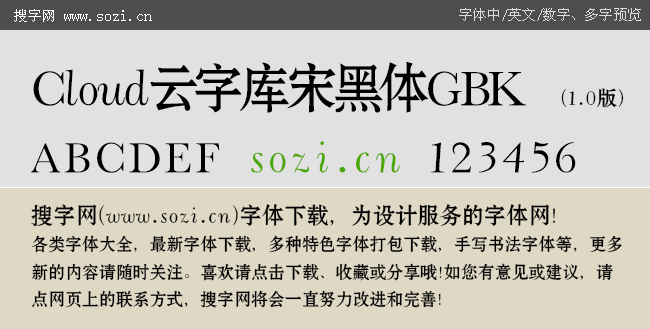
Cloud云字庫宋黑體GBK
搜字網(wǎng)提供一款Cloud云字庫宋黑體GBK中文字體下載,Cloud云字庫宋黑體GBK是一款非常大方的宋黑字體,簡潔大方,整體效果十分出色,GBK碼包含字體更全,適合應(yīng)用于廣告設(shè)計(jì)、名片設(shè)計(jì)、包裝印刷、兒童產(chǎn)品設(shè)計(jì)等應(yīng)用。